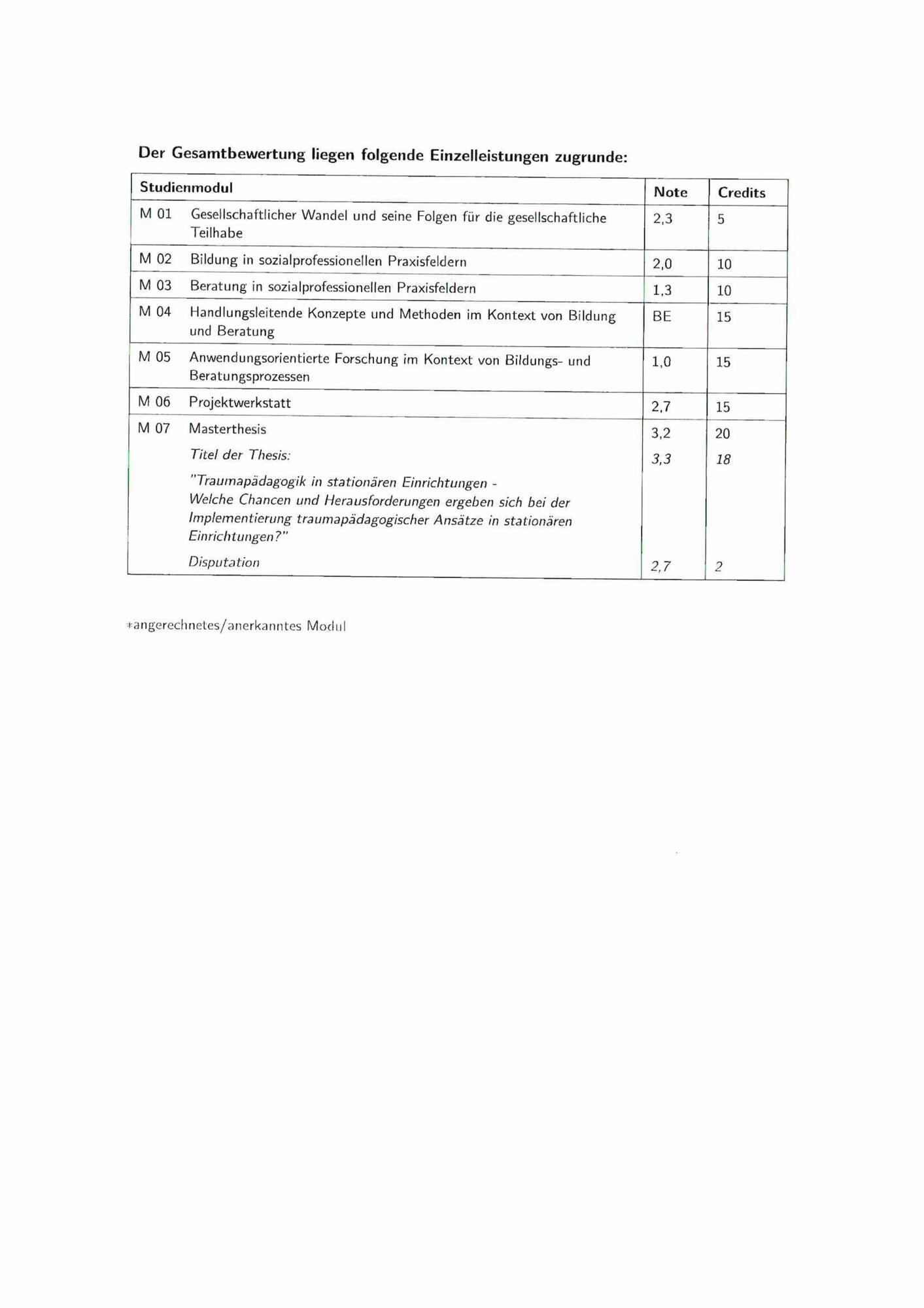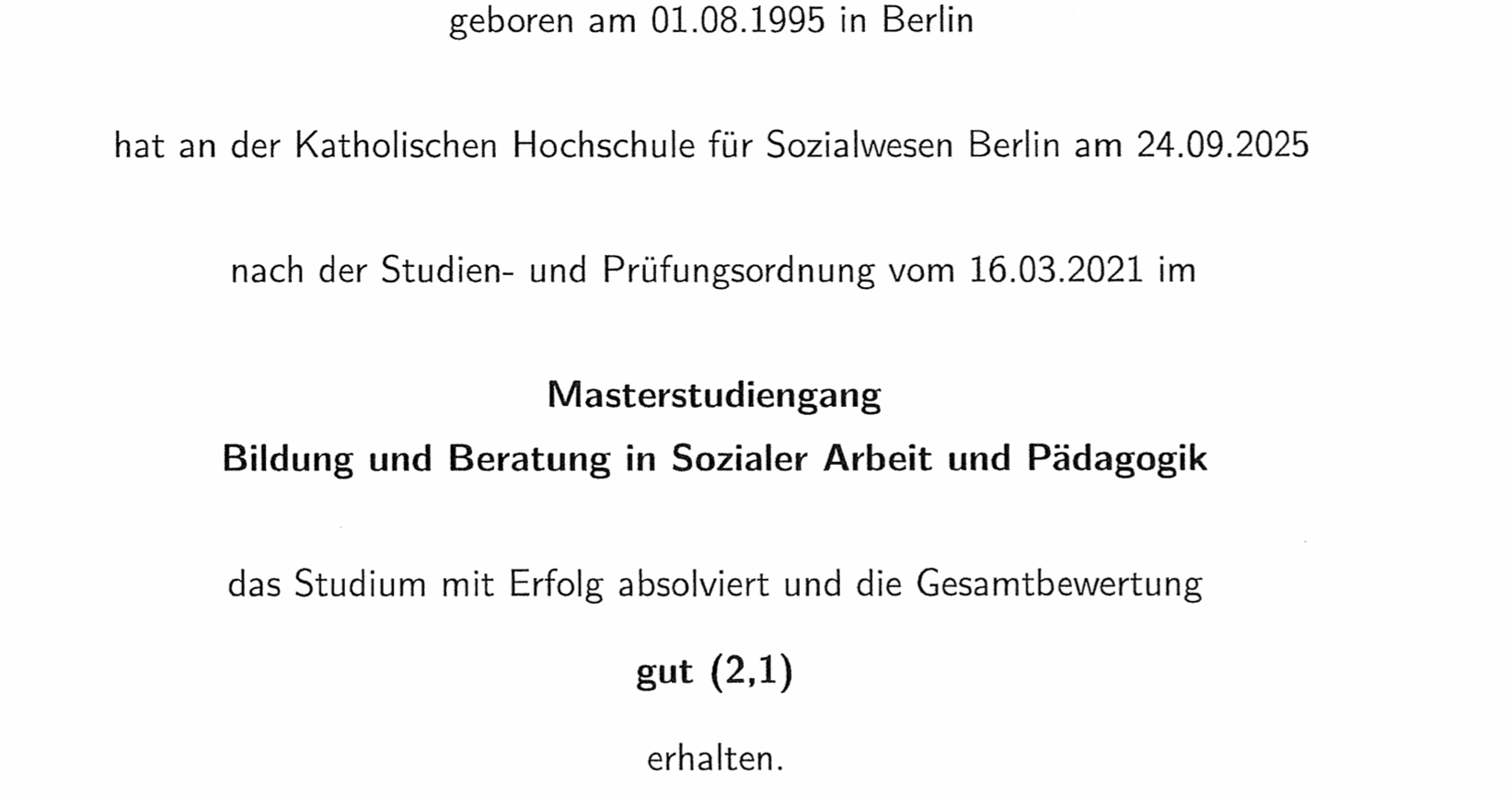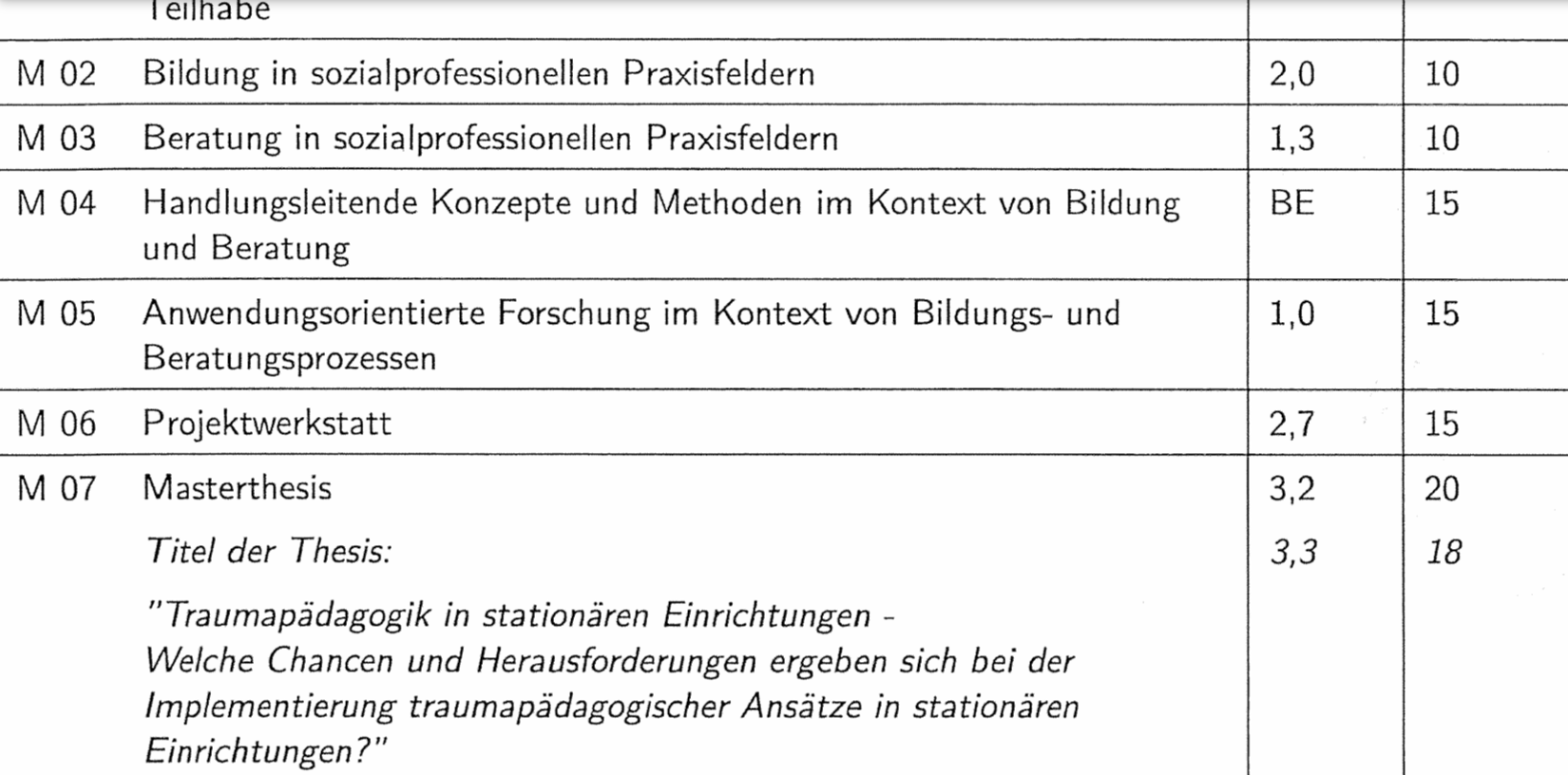
Suche Schriftart eines Master-Zeugnisses (KHSB Berlin) für Hochzeitseinladungen
ich bin auf der Suche nach der exakten Schriftart, die auf einem offiziellen Dokument verwendet wurde, und hoffe auf euer geschultes Auge. Mir gefällt das elegante und filigrane Design der Buchstaben so gut, dass ich diese Schriftart unbedingt für meine kommenden Hochzeitseinladungen nutzen möchte.
Besondere Merkmale, die mir bereits aufgefallen sind:
- Es handelt sich um eine Schrift mit dezenten, aber sichtbaren Strichstärkenkontrasten (ähnlich einer humanistischen Grotesk oder Inzise).
- Das kleine „g“: Es ist zweistöckig (wie eine 8 geformt) und besitzt einen feinen, kleinen Haken (Ohr) oben rechts.
- Das kleine „a“: Zweistöckig, mit einem auffällig großen Abstand zwischen dem Bauch und dem oberen Bogen.
- Das große „M“: Die vertikalen Außenstriche schließen oben absolut flach und eben ab.
- Kontraste (z. B. beim „B“ und „t“): Die Strichstärken sind leicht ungleichmäßig. Beim großen „B“ ist der horizontale Mittelstrich, der die beiden Bögen trennt, beispielsweise sehr filigran.